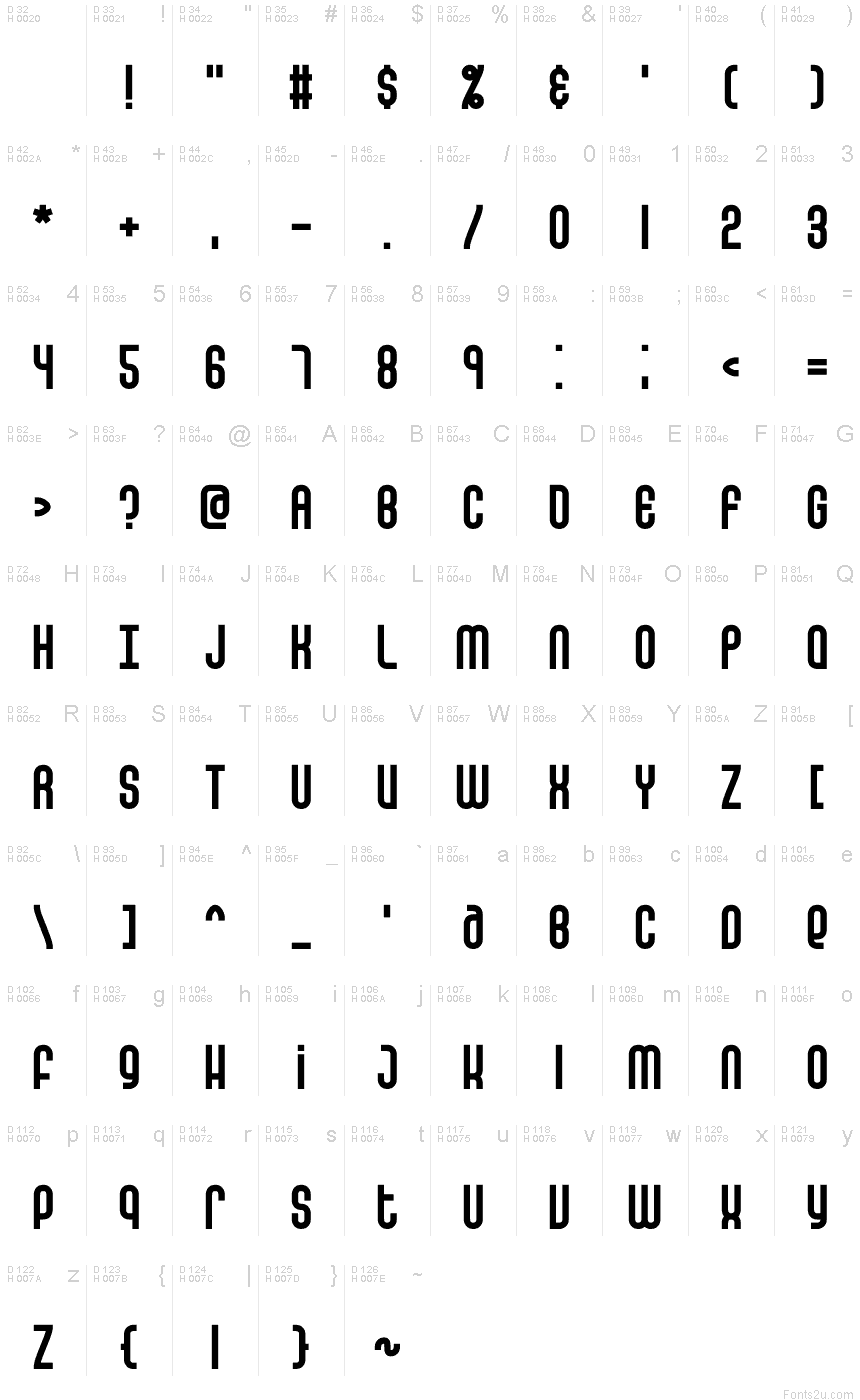
False Positive BRK
False Positive BRK od Aenigma Fonts to nowoczesny krój displayowy. Wysokie, ultrawąskie litery tworzą smoliście czarne kolumny o łagodnie zaokrąglonych narożnikach i kwadratowych wnętrzach, nadając każdemu słowu futurystyczny, blokowy charakter. Rytm jest zwarty i mechaniczny – linie przypominają raczej ciągi kodu lub neony niż klasyczny tekst, dzięki czemu krój natychmiast przyciąga wzrok na każdym tle.
Dzięki False Positive BRK, pogrubione tytuły łączą się niczym modułowe kafelki – to świetny wybór do plakatów sci-fi, okładek albumów techno, logotypów e-sportowych, ulotek, identyfikacji wizualnej wydarzeń oraz eksperymentalnych projektów opakowań. Ten font doskonale sprawdza się w dużych rozmiarach, gdzie jego gęste, pionowe formy dominują w kompozycji. Połącz go z prostym krojem bezszeryfowym w tekstach głównych albo użyj False Positive BRK do wszystkiego, dodając większe odstępy, aby uzyskać wyraziste, mocne nagłówki.